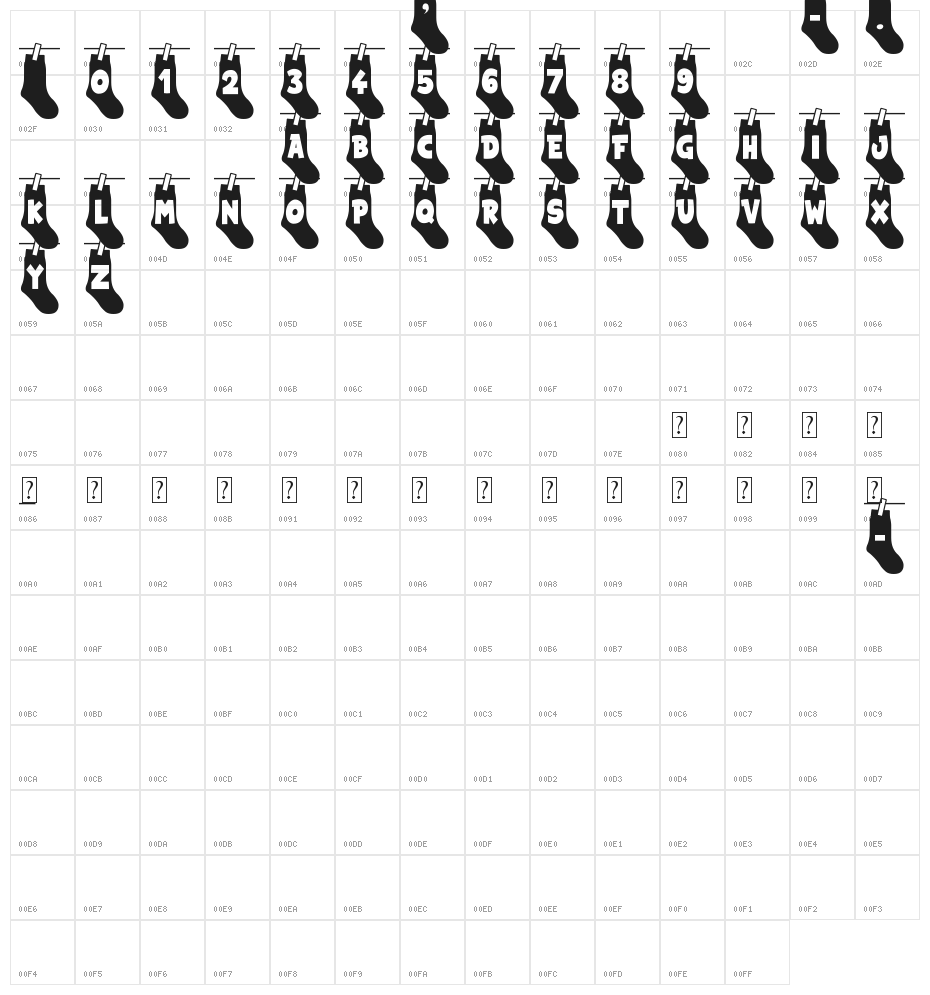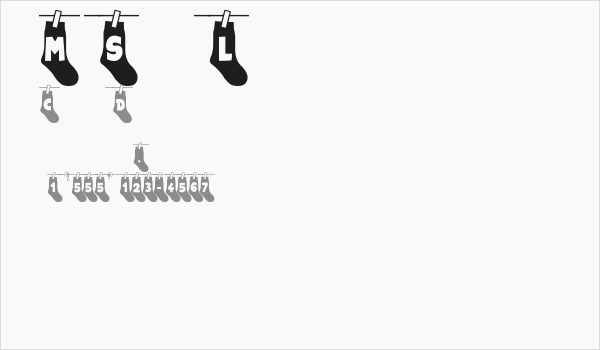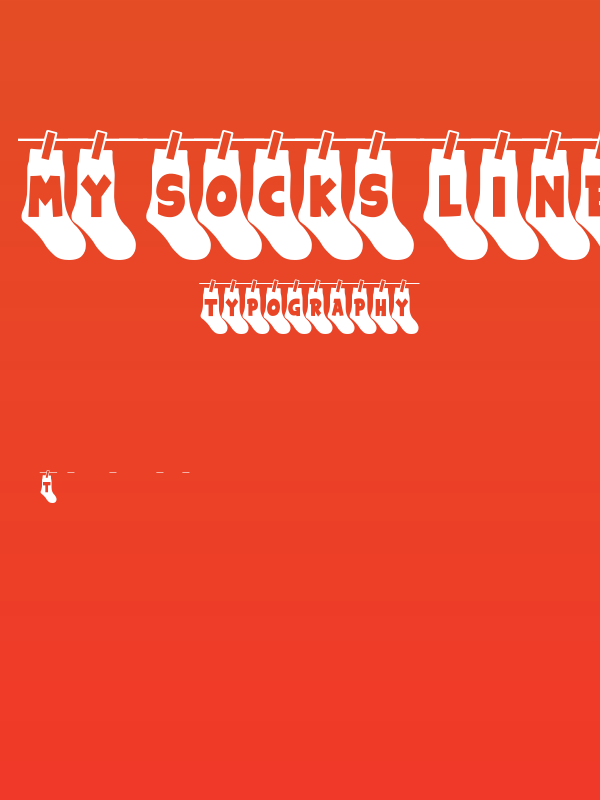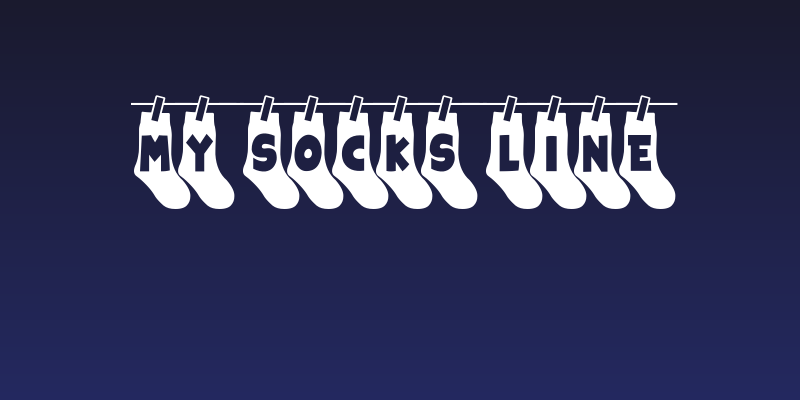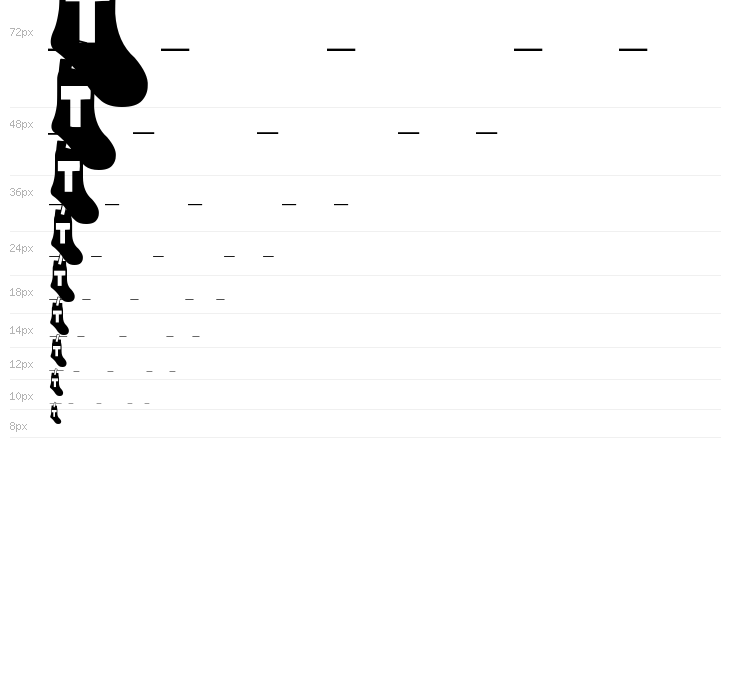
My Socks Line Font
| Gesamtstil | Playful, Whimsical |
| Vorgeschlagene Projekte | Ideal for children's books, playful branding, party invitations, and themed event posters. |